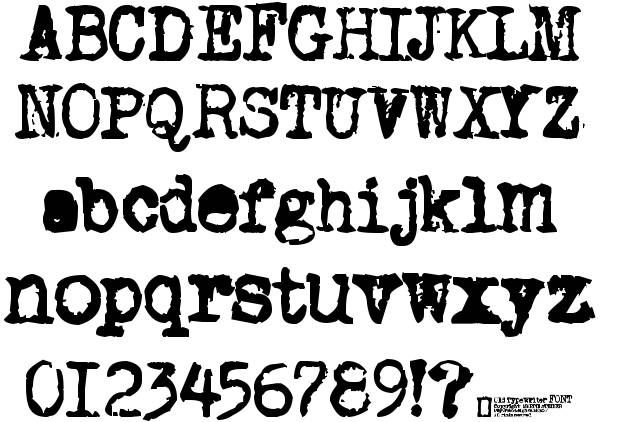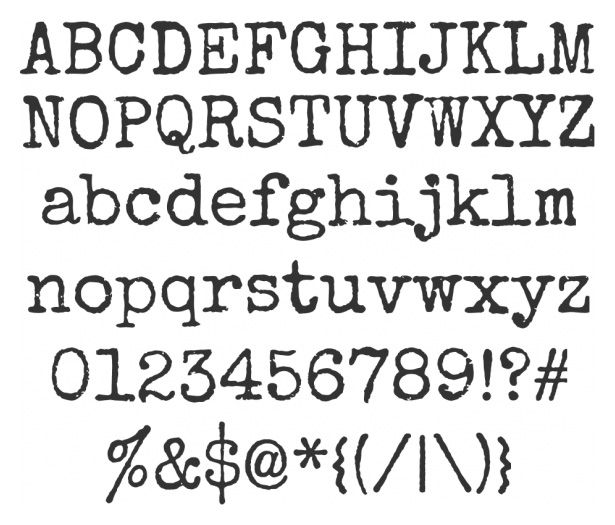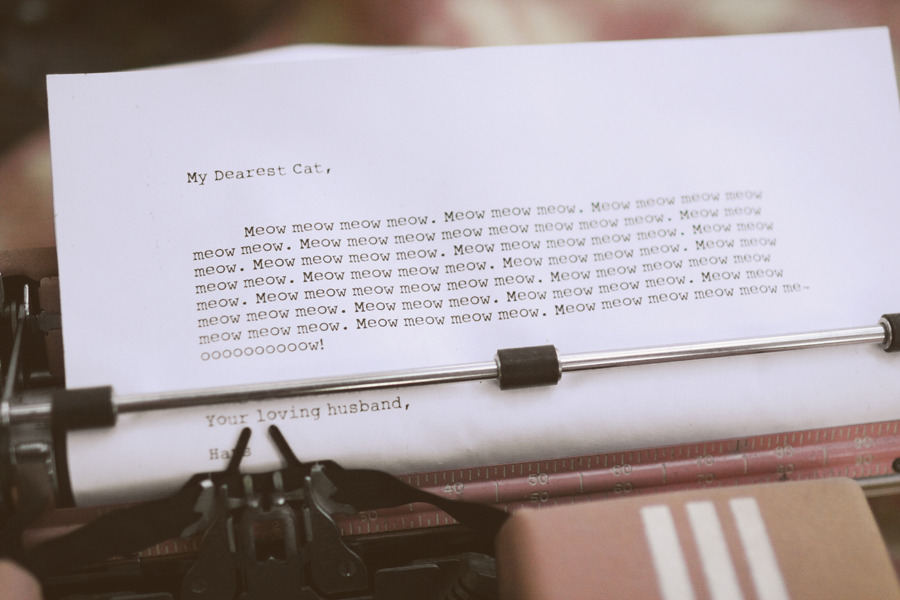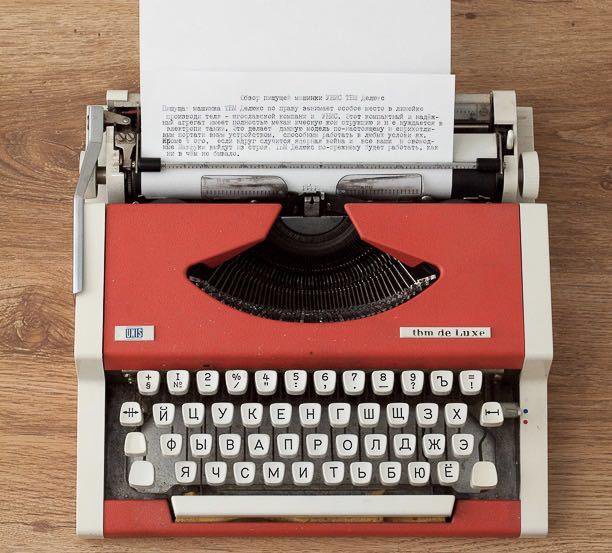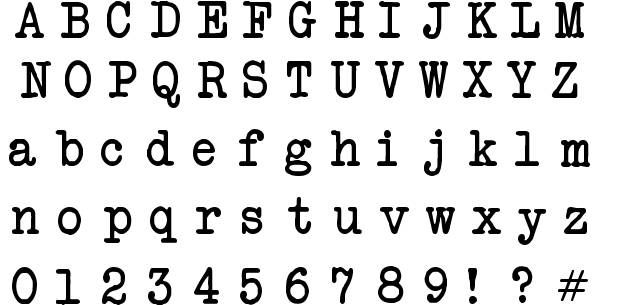
8 лучших шрифтов для пишущих машинок
Хотя они перестали использоваться несколько лет назад, есть еще меланхолики, которые хотят восстановить машинопись, не только как декоративный элемент, но и как хобби, в котором можно восстановить машину и использовать ее.
Нажатие каждой из его клавиш было усилием, которое многие креативщики, начинающие сейчас в мире дизайна, никогда не получат. И это то, типографика машинок необходимый элемент при оформлении, смотря какие тексты.
Многим дизайнерам, не имеющим доступа к таким машинам, необходимо найти правильный шрифт, сохраняющий суть печатной машинки, старого, поэтому сегодня мы собираем подборку лучших шрифты пишущей машинки.
Что такое шрифты для пишущих машинок?
Машинописный шрифт, или, как его еще называют, машинописный шрифт, является одним из чаще всего используется при работе над винтажными дизайнами. Хотя пишущие машинки уже давно вышли из дизайнерских студий, любителей этого шрифта много.
Есть несколько машинописных шрифтов, то есть каждый из них имеет вариации. Шрифт, который обычно используется для имитации оригинального шрифта, представляет собой типографика с классическим потертым видом, с небольшим количеством текстуры.
Это шрифт с одним общим аспектом, несмотря на его вариации, он имеет одинаковая и постоянная ширина между палочками и засечками. Как мы уже говорили, эти шрифты вдохновлены старыми пишущими машинками.
До компьютеров было очень распространено печатать для общения, будь то личные и деловые письма, приглашения, уведомления и т.
д. Сегодня его использование ограничено временем верстки. книги для заголовков или когда вы хотите придать графическому произведению формальный или винтажный стиль.
Далее мы собираемся показать вам выбор разных шрифтов для пишущей машинки так что у вас есть разные ссылки в вашем типографском каталоге.
Американская пишущая машинка
Он появился в 1974 году благодаря Джоэлу Кандену и Тони Стэну, которые создали этот алфавит, имитирующий шрифты, используемые на пишущих машинках. Он сочетает в себе жесткость старых шрифтов с современным стилем.
Курьер
Гарнитура Courier, созданная Говардом Г. Кеттлером в 1995 году для IBM. является одним из самых известных в мире. Это был шрифт, предназначенный для пишущих машинок, поэтому его символы занимают одинаковую ширину, и именно по этой причине строки текста, написанные этим шрифтом, неоднородны, то есть буква m имеет тот же пробел, что и буква i, например.
Именно благодаря этим недостаткам шрифт Courier так хорошо известен в мире дизайна и используется до сих пор.
Позже Адриан Фрутигер переработал его для IBM Selectic Microsoft, чтобы его можно было использовать в Интернете. Это шрифт, который уже установлен как на MacOs, так и на Windows.
Люсида Пишущая машинка
Пишущая машинка Lucida принадлежит к семейству Lucida. Он был создан Чарльзом Бигелоу и Крисом Холмсом в 1985 году. Этот шрифт был одним из первых шрифтов для цифровых пишущих машинок.
Этот шрифт имеет небольшие и тонкие изменения толщины его рогов и отличная читаемость. Это тяжелый, но четкий шрифт при чтении.
Компост
Одна из типографских работ Нильса Томсена. Comspot пытается восстановить классические формы машинных шрифтов написания старых, но адаптации их с человеческим оттенком.
Он был разработан в 2015 году как корпоративный шрифт для Comspot, дистрибьютора оборудования и программного обеспечения.
В принципе, было необходимо всего три песо, но для редакционного использования их число было увеличено до девяти. Эти гири вдохновлены историей компании, первоначально коды программирования.
Офис Санс
Разработан в 1990 году Эриком Шпикерманном. Officina Sans — это шрифт, чей Цель состояла в том, чтобы эффективно общаться в формах компаний и офисов. В стиле, основанном на шрифтах старых пишущих машинок, но с более современным и технологичным видом.
Шрифт Officina имеет два подсемейства; Officina Sans без навершия и Offica с навершием. Первоначально для использования в офисах у него было всего два песо, но по мере развития его использования в рекламных кампаниях ему необходимо было увеличить свой вес. Это типографика с отличной удобочитаемостью благодаря интервалам, высоте X и формам.
Диссертация Пишущая машинка
Это платный шрифт и очень хороший выбор при поиске шрифтов для пишущих машинок.
У пишущей машинки есть три разных веса, жирный, обычный и третий, называемый усталым, является наиболее интересным из трех, так как придает буквам текстуру, придавая им винтажный стиль.
Аминта
Гарет Хейг, дизайнер шрифтов, является создателем Aminta, шрифта, который оригинально сочетает в себе классический стиль старых пишущих машинок с современной атмосферой Шрифт Гельветика.
12. Аволаджойн
Avolajoin — это шрифт для пишущей машинки, который не будет выглядеть неуместным на страницах комикса. Его линии толстые, а границы букв рассеяны. Общий эффект отличный, если вы хотите оставить впечатление в заголовке или в дизайне. Однако шрифт не очень подходит для мелкого шрифта.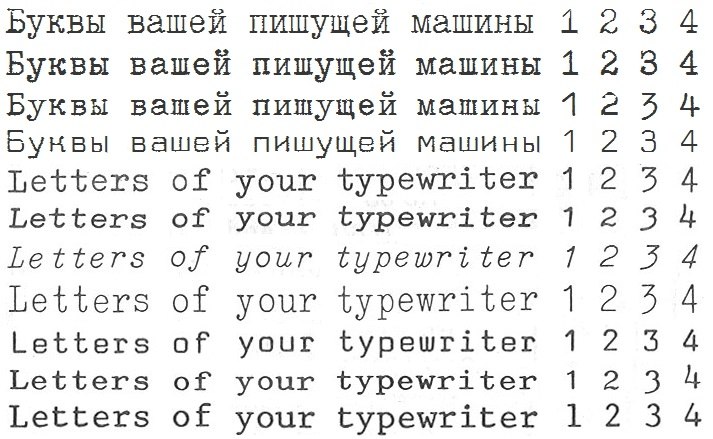